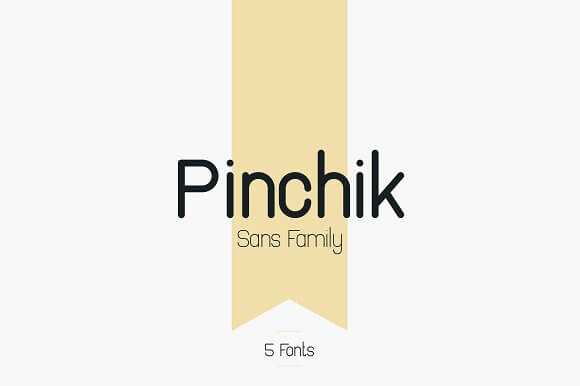
免費英文字體下載 Pinchik 具備乾淨且圓潤的無襯線字體
Pinchik Font 01
這款免費的英文字體 Pinchik 是由 Vlad Fedotov 設計的,它是一款乾淨且圓潤的英文字體,採用無襯線的字體設計,這款字體一共有 5 種變化以及多語言的支持,它是一種通用型的字體,不論用在內文或是標題上都很適合
Pinchik Font 02
Pinchik Font 04
Pinchik Font 05
Pinchik Font 06
Pinchik Font 07
Pinchik Font 08
Pinchik Font 09